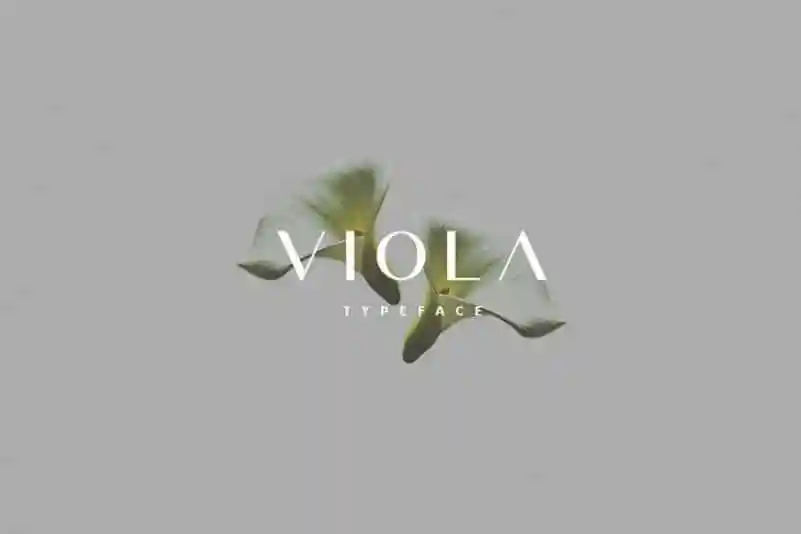
Viola Sans Serif é uma elegante tipografia do tipo linear criada por Hadenartwork®, especialmente projetada para se encaixar em uma variedade de projetos, desde a moda e as revistas até os anúncios e as cartas de visita. Este estilo moderno mantém o charme clássico, tornando-o perfeito para aplicações variadas como logomarcas, identidades de marca, fotografias, convites de casamento, citações em blogs, cabeçalhos de posters, cartazes, livros e sites. Viola Sans Serif é a escolha ideal para quem busca um visual moderno com um toque de sofisticação clássica. Não importa qual seja seu próximo projeto, essa fonte será uma excelente opção.